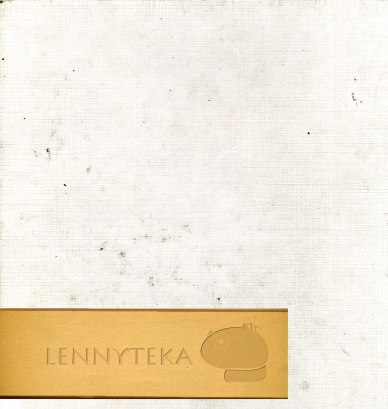
Tipografia Decorativa
يأتي منتج رقمي بعنوان Tipografía Decorativa ليأخذ القارئ في رحلة بصرية مميزة داخل عالم الحروف، حيث لا تقتصر الكتابة هنا على وظيفتها التقليدية كوسيلة لنقل الكلمات، بل تتحول إلى عنصر جمالي وزخرفي يُضفي على التصميم قيمة إضافية ولمسة إبداعية خاصة. هذا الكتاب الإلكتروني يُقدَّم كمرجع غني يبرز كيف يمكن للطباعة الزخرفية أن تتجاوز حدود النص المكتوب لتصبح جزءًا أساسيًا من الهوية البصرية والتواصل الفني.
إن Tipografía Decorativa كمنتج رقمي يُسلّط الضوء على تنوع الأساليب والأنماط التي يمكن أن تتخذها الحروف، وكيفية دمجها في الأعمال التصميمية بطريقة متوازنة بين الجمال والوضوح. فهو يكشف عن أسرار التكوينات الزخرفية للحروف، واستعمالها في الملصقات، الشعارات، الأغلفة، والوسائط الإعلانية بحيث تمنح العمل شخصية فريدة تترك أثرًا بصريًا قويًا.
يمثل هذا الكتاب الإلكتروني دليلاً عمليًا ومرجعًا إلهاميًا في الوقت نفسه، فهو يخاطب الطلاب والمبتدئين الراغبين في استكشاف مجال الطباعة الزخرفية من بداياته، كما يخاطب المصممين المحترفين الذين يبحثون عن تطوير مهاراتهم واستلهام أفكار جديدة لإثراء مشاريعهم. فهو يوضح كيف يمكن للمصمم أن يبتكر حروفًا تُشبه الأعمال الفنية المصغرة، وكيفية استخدامها بشكل مدروس يعزز الرسالة البصرية ولا يطغى عليها.
وبفضل كونه منتجًا رقميًا، فإن Tipografía Decorativa يمنح القارئ سهولة الوصول إلى محتواه في أي وقت ومن أي مكان، مما يجعله رفيقًا مثاليًا في مسيرة الإبداع والتعلم. إن القيمة الكبرى لهذا المرجع تكمن في كونه يفتح أبوابًا جديدة لفهم الطباعة كفن بصري قائم بذاته، لا يقتصر على القراءة بل يضيف عمقًا وجمالًا لأي مشروع تصميمي.
وباختصار، يُعد Tipografía Decorativa منتجًا رقميًا متكاملًا يجمع بين المتعة البصرية والمعرفة النظرية، ويلهم القارئ لاستكشاف الإمكانات اللامحدودة التي يمكن أن تقدمها الحروف حين تتحول إلى أداة زخرفية تحمل روح الإبداع والفن.